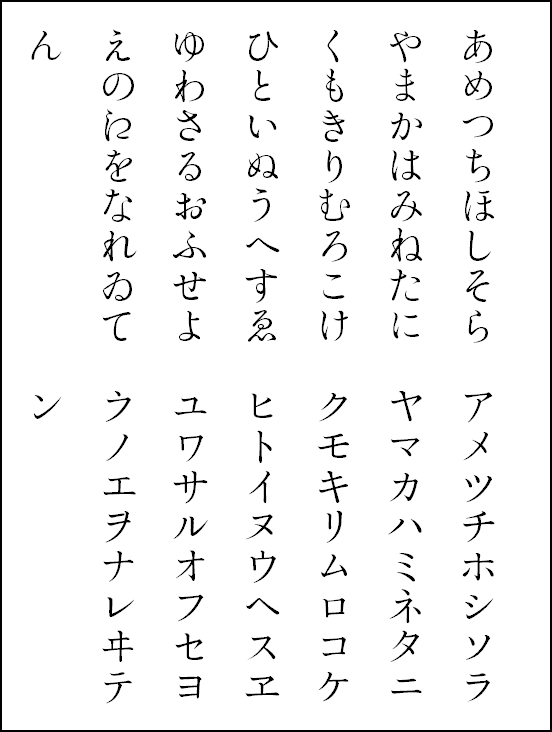
錦明朝かな
「錦(にしき)明朝かな」は明朝体の仮名文字専用フリーフォントです。
さらら明朝や錦源明朝の仮名文字だけを単独フォント化したものに相当します。
錦明朝かな version 4.000の仕様
- 句読点
- R見本(ひらがな・カタカナ)
錦明朝かなの改訂履歴
- 4.000 (20230523):
全体的に骨格を見直しました。大きな変更点は次の通りです。
- Version 1.200以降、「ま」の1画目は2画目より長くなっていましたが、築地体後期五号由来の「1画目のほうが短い形」に戻しました。
- 「ふ」「𛀁」の1画目の点を、時計回りから反時計回りに変更。
- 「ヲ」を石井明朝OKLやA1明朝風の「1画目と3画目が離れていて、かつ2画目が3画目を貫いている形(ニ+ノ)」に変更。
その他、小さい「こ」「コ」がUnicode 15で符号化されたことを受けてCMapも更新しました。
- 3.004 (20210830): アウトラインの調整
- 3.003 (20210830):
- カタカナを中心にアウトラインの微調整。
- GSUBデータの増補。
- 3.002 (20210828):
- Regular, Medium, SemiBold, Boldの4ウェイトを追加。
- 3.002 (20210824):
- U+3008~U+301F付近の括弧類を一旦削除(多ウェイト化が済んだ際には多分復活させます)。
- 3.001 (20210816):
- 3.000 (20210516):
- ひらがな・カタカナの全グリフについてアウトラインの見直し。
- 小さいゐゑヰヱを追加。
- 2.000 (20201204):
- 膨らみがない起筆部(「い」の2画目など)の形状を変更。
- ひらがなを中心にアウトラインの見直し。
- 欧文グリフを削除し、純粋な仮名文字フォントに変更。
- CIDの並びを錦明朝・錦源明朝などと共通化。
- 1.230 (20181213): 仮名グリフにヒンティング情報を付加。0︀ (slashed zero) 用のUVSを追加。
- 1.222 (20130630)
- 1.221 (20130615): コンパイル時オプションの変更。
- 1.220 (20130608)
- 1.211 (20130504)
- 1.210 (20120624): ‼⁉⁇⁈の4文字を追加。OS/2.ulUnicodeRange[1-4]の情報を更新。
- 1.200 (20120519): 括弧類の追加。
- 1.110 (20120422): プロポーショナルメトリクス情報 (palt) の追加。
- 1.101 (20120418)
- 1.100 (20120415)
- 1.002 (20110911): Windows-1252用グリフの追加(U+2026: 三点リーダを除く)。
- 1.001 (20110831): 線の端の処理を変更。Basic Latin用グリフの追加。
- 1.000 (20110724): fontRevisionを1.000に変更。行間を20%から80%に変更。
- 0.900 (20110505): 最初のリリース。
グリフ品質の改善、アウトラインの修正に関する記述は省略してあります。